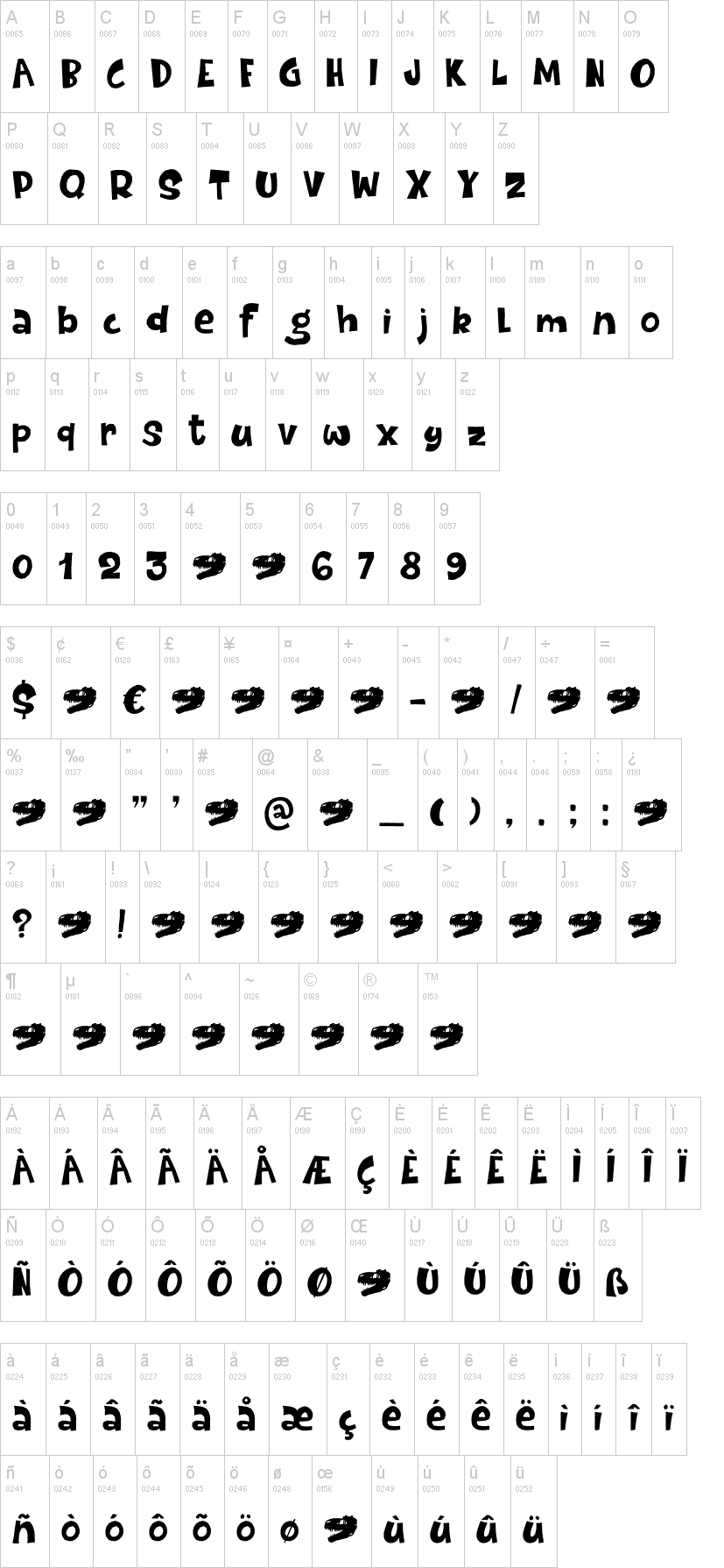
吧 Dinosaur Cake 是一款由 Fontfabric 公司推出的一款免费字体,它拥有一种古老的外观,适合各种应用场景,从海报到书籍,甚至于网页设计都能使用。这款字体拥有粗体、斜体和两种粗斜体,共有 5 个字重,支持多种语言,可以满足不同需求。它的整体外观比较粗糙,适合表达激情和热情,但也可以用来表达冷静和沉稳的气氛。内容介绍
Dinosaur Cake是一款非常不错的手写艺术字体,具有很好的视觉感,适合于文化类的宣传设计、商业类品牌的广告和产品包装设计以及个性化文字排版等较多场景。